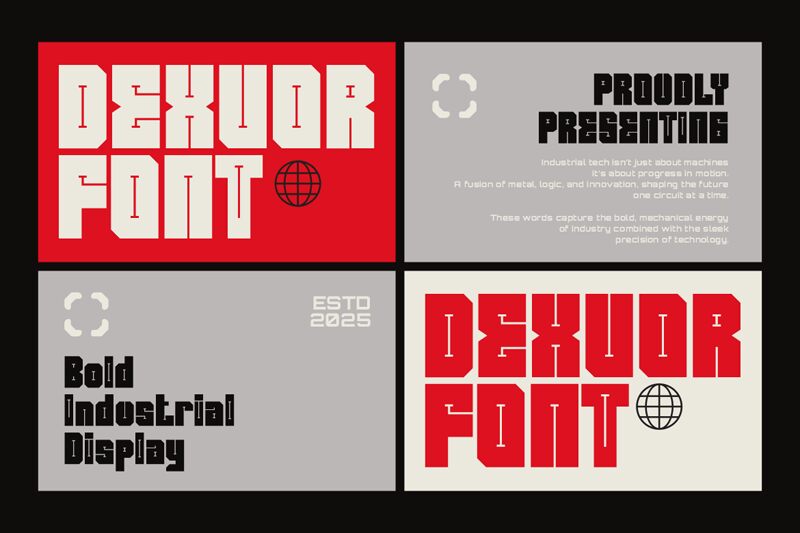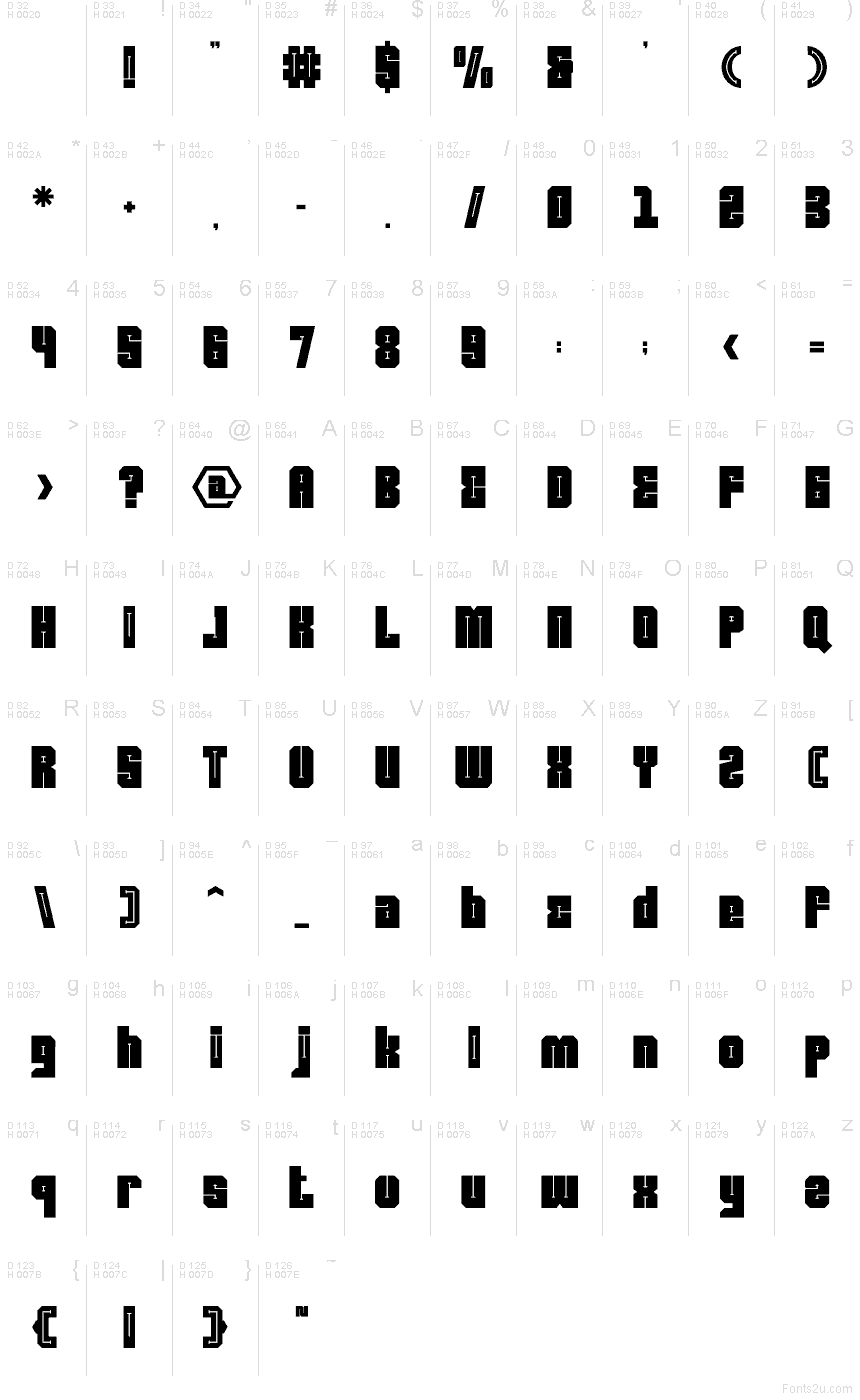
Dexvor, creada por Shanaf Studio en 2025, es una tipografía techno de visualización gratuita construida con formas de letras masivas y cuadradas. Las esquinas pronunciadas, los bordes recortados y los finos trazos internos confieren a las mayúsculas el aspecto de paneles industriales marcados con circuitos simples.
El público de los juegos de arcade y de la música electrónica reconocerá su actitud maquinizada en títulos de crédito y carteles de eventos, especialmente para lanzamientos, torneos y noches de club. Las siluetas anchas también se adaptan a la mercancía de ropa urbana y a la identidad visual de locales orientados a la tecnología. En esos entornos, cada letra puede actuar como un componente etiquetado de un panel de control en lugar de como texto neutral.